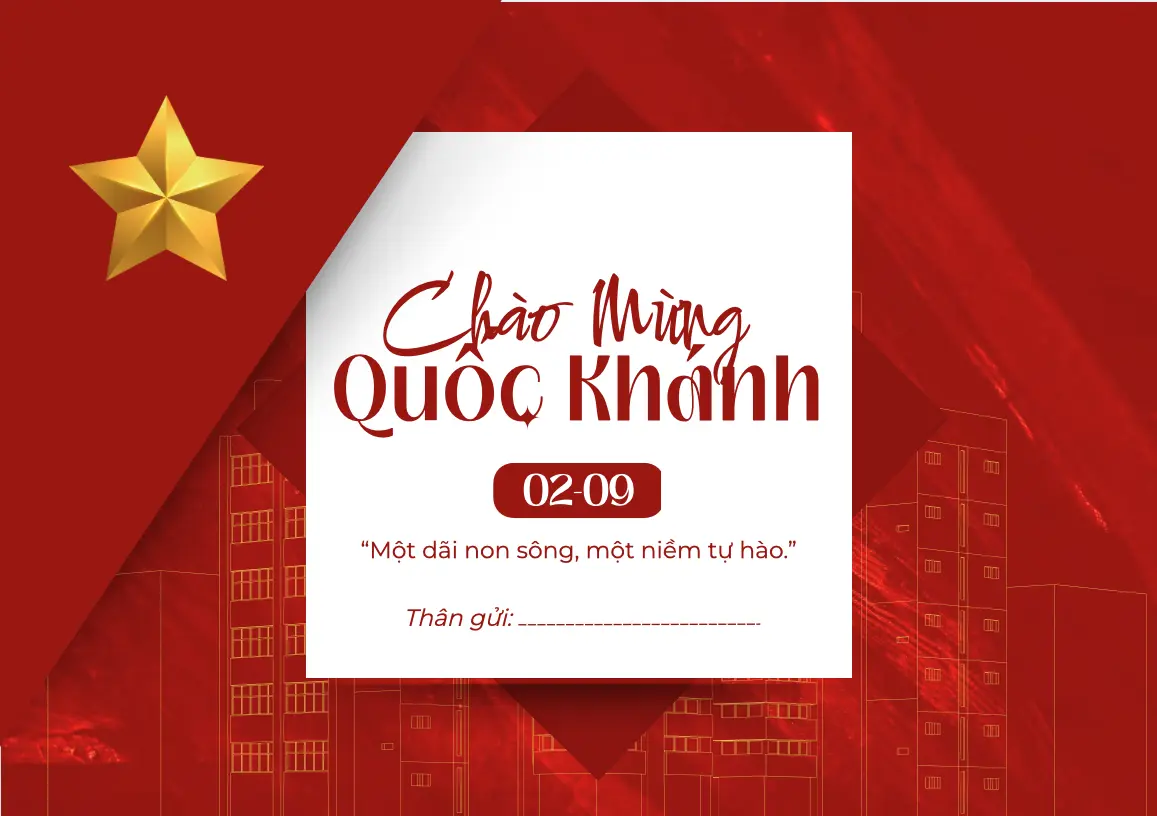
Tên font: Font Việt hoá Mesdag (Bộ 4 font)
Font PCMP Mesdag Việt hóa
Font PCMP Mesdag Việt hóa là sự kết hợp độc đáo giữa sans serif, serif và handwritten, mang đến một kiểu chữ hiện đại, cá tính và đầy phong cách. Bộ font này gồm 3 style chữ, được trang bị Alternates và Discretionary Ligatures giúp các ký tự liên kết mượt mà, tự nhiên. Ngoài ra, PCMP Mesdag còn có phiên bản Variable, hỗ trợ đa ngôn ngữ, chữ số và ký hiệu tiền tệ.
Với thiết kế linh hoạt, PCMP Mesdag phù hợp cho nhiều mục đích sáng tạo như: tạp chí, tiêu đề, poster, logo, thiệp mời, postcard, trích dẫn, dự án DIY, thiết kế phong cách vintage, hoài cổ thập niên 60s, 70s, 80s, dự án cưới hỏi và nhiều hơn thế nữa.
Nhà thiết kế: Kadek Mahardika